科幻目前已经发展成为了一种文化和风格,科幻文化也成为了一种由科幻作品衍变出来的新文化。科幻为人们提供了想象的平台,文学文化交流的平台。对于“科幻的”定义更是众说纷纭。科幻最重要的就是科技感、超现实感,在很多设计领域都可以看到科幻风格的身影,字体的选择会偏向于较为冷峻的字体,来塑造异次元的特征,例如下面字体图片:
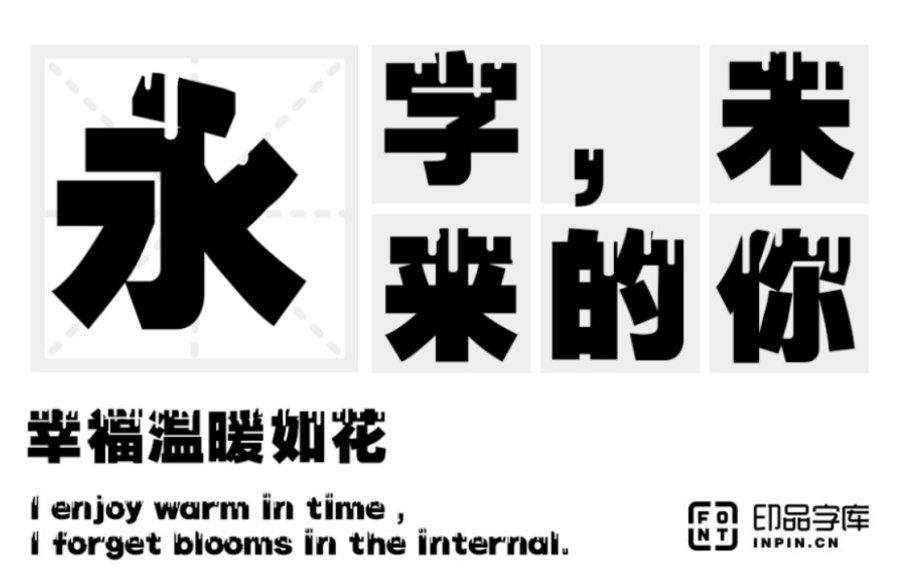
印品油漆体:这款字体在字形设计上采用了超粗黑体的基本笔形,参以油漆的创意、形态,婉转有度,超脱时代的气息。增添了视觉立体感,可广泛应用于宣传、广告、商标、标语、黑板报以及商品包装和装潢、报刊杂志和书籍的装帖上等领域。
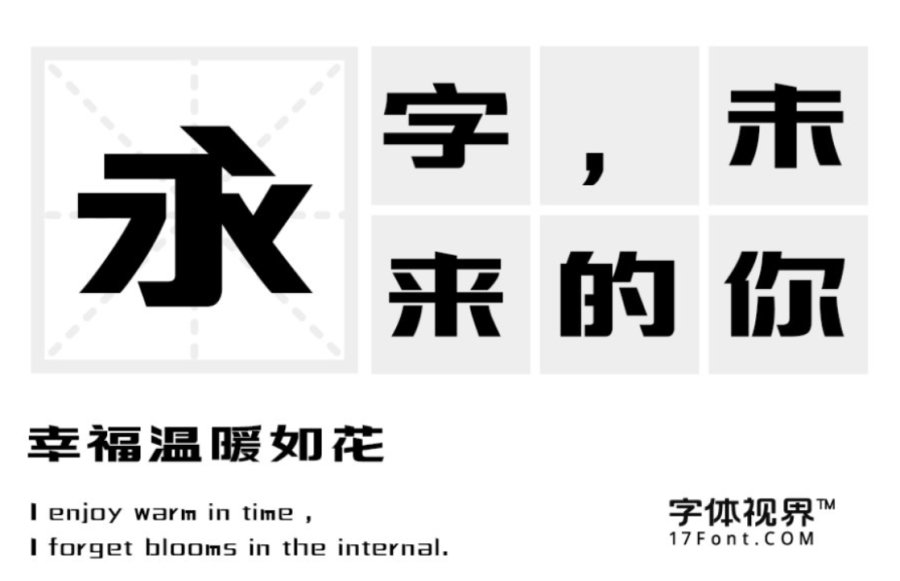
三极智量黑简体:这款字体字形扁方、结构严谨,笔画粗壮、左右结构有意夸张,富有张力。结构新颖独特、个性刚健有力,给人一种气势雄伟,冷峻的感觉。还适用于商业品牌的广告、产品包装设计、影视作品,界面设计等领域。
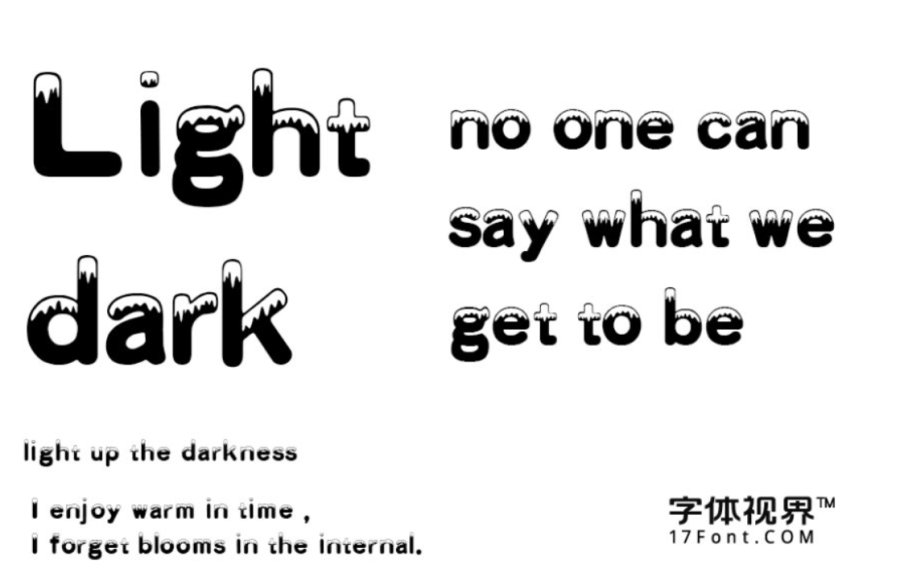
Karna:Karna字体是一款立体字,有积雪效果像一座高不可攀的险峻冰山,黑白对比强烈。字形结构丰满,视觉效果丰富。在兼具科技感的同时不失辨认度,字形清晰易于图片识别字体。适用于广告,包装,报纸印刷,屏幕显示等领域。